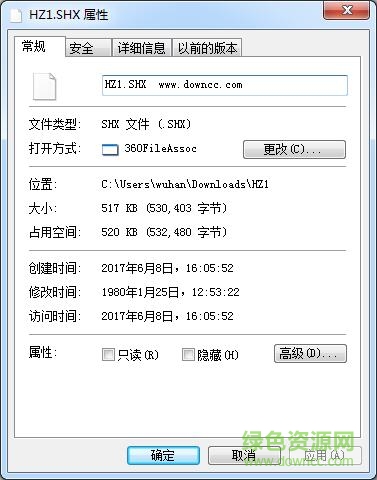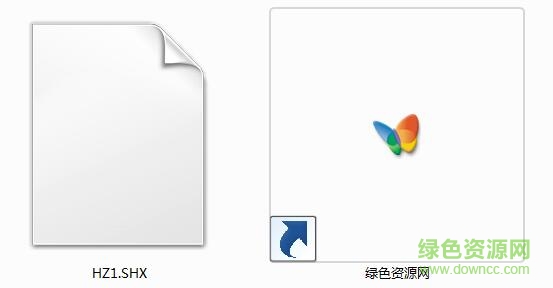
hz1.shx字體是一個免費的CAD藝術(shù)類字體。再autocad中經(jīng)常用到!小編提供的這款字體是完全免費的,對于cad設(shè)計行業(yè)的朋友很有幫助哦??靵肀菊灸米甙伞?/p>
hz1.shx字體是一款非常美觀的cad字體應(yīng)用!通過這些字體能夠在CAD中進行輸入和寫文字,讓用戶更好的標注CAD中的圖紙。需要的用戶歡迎在綠色資源網(wǎng)下載。